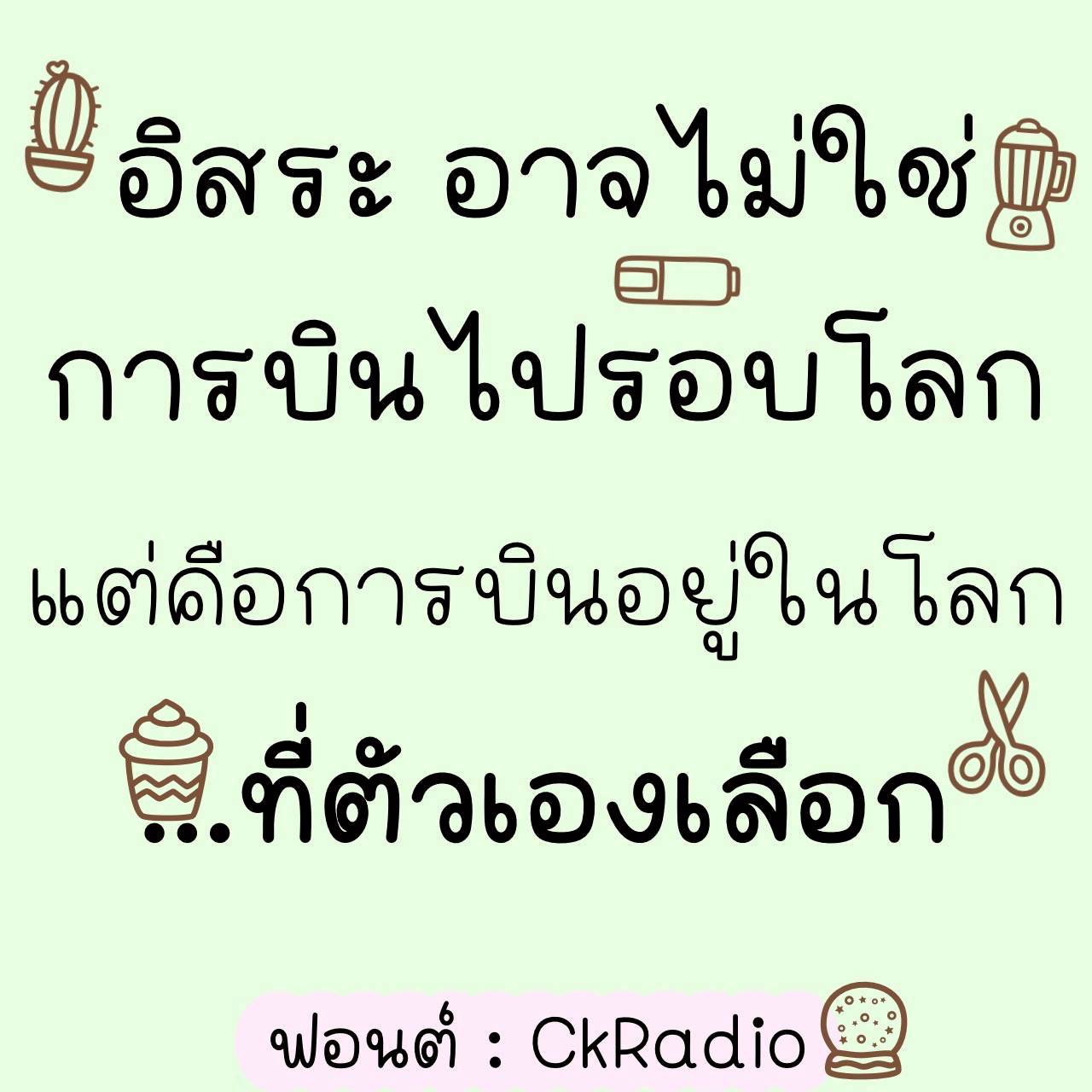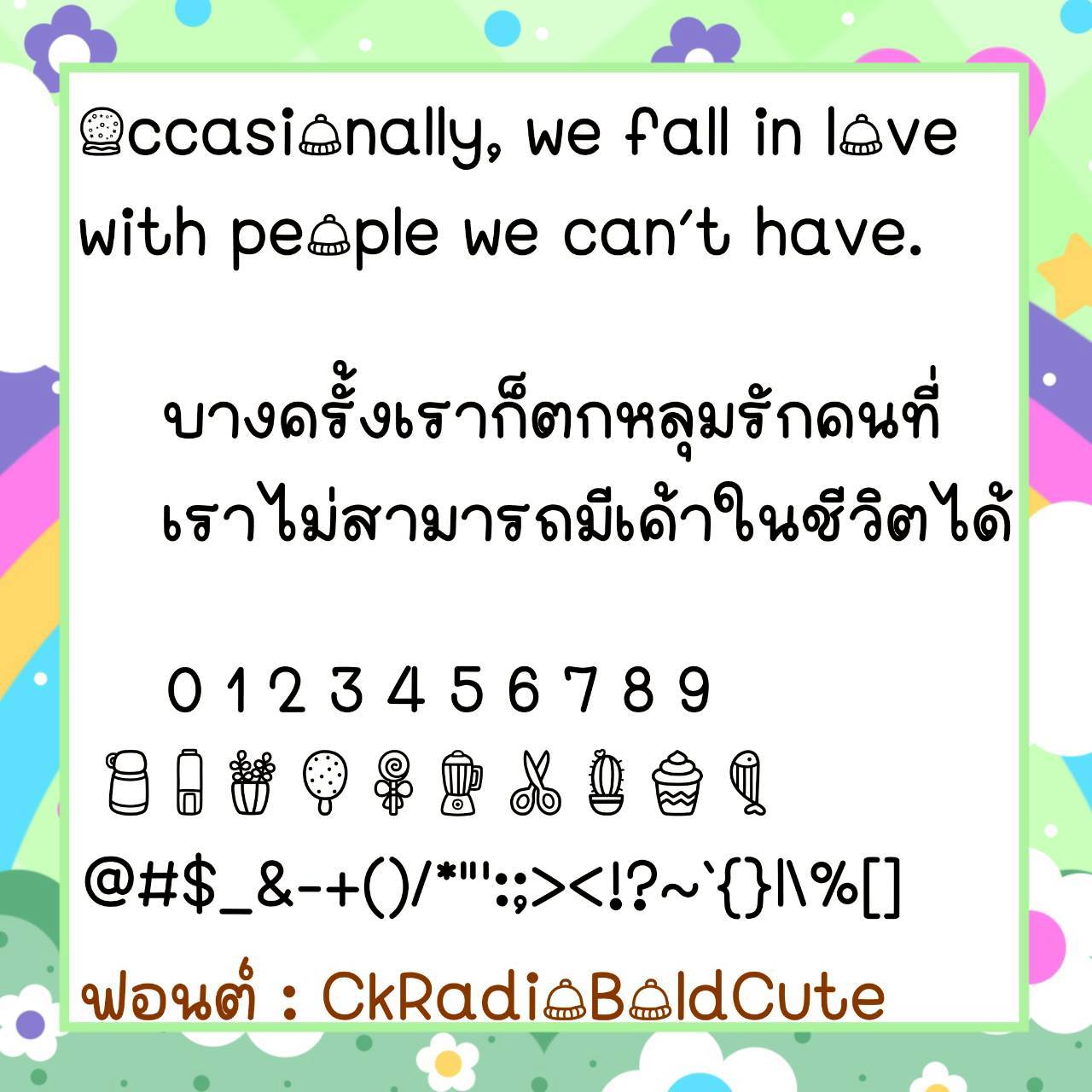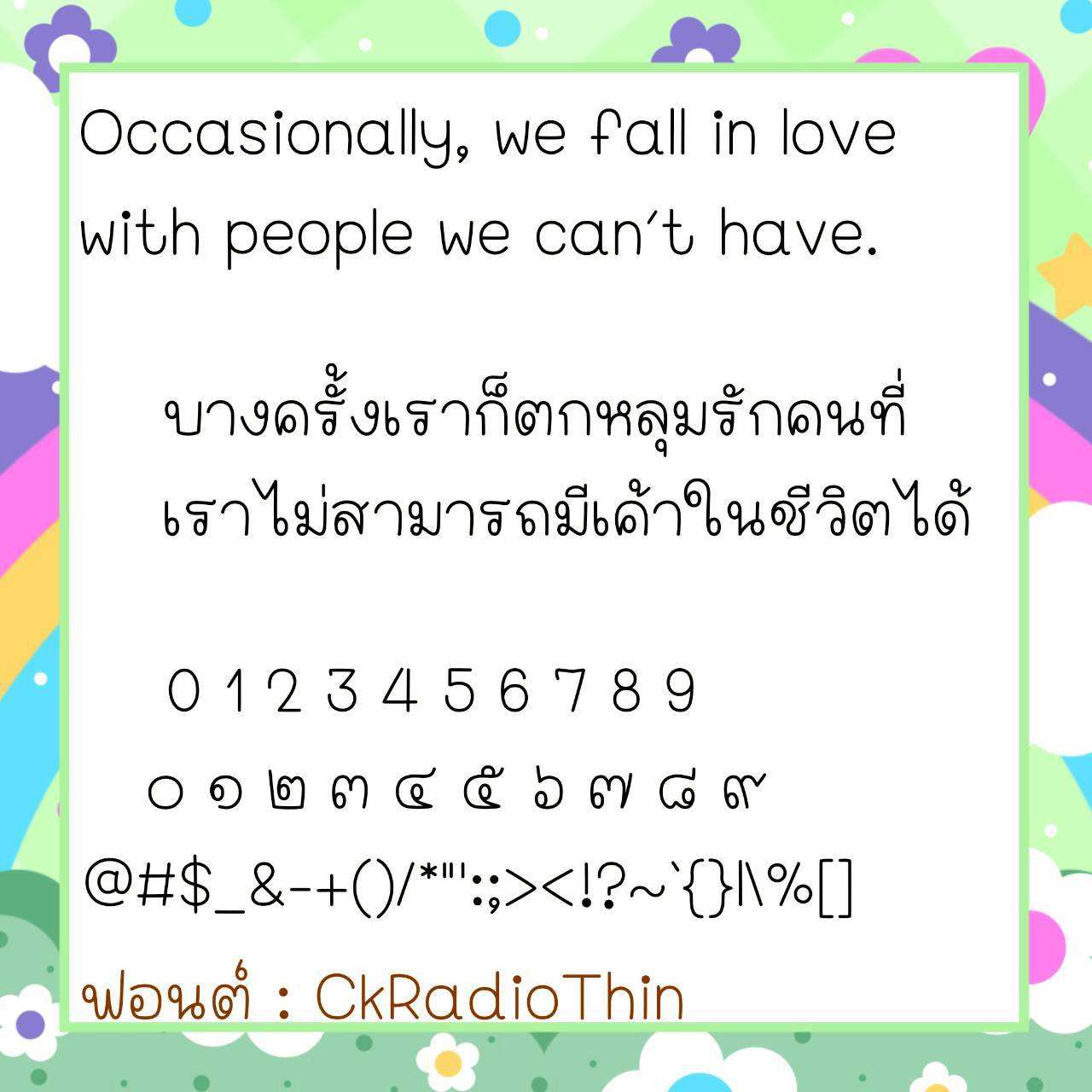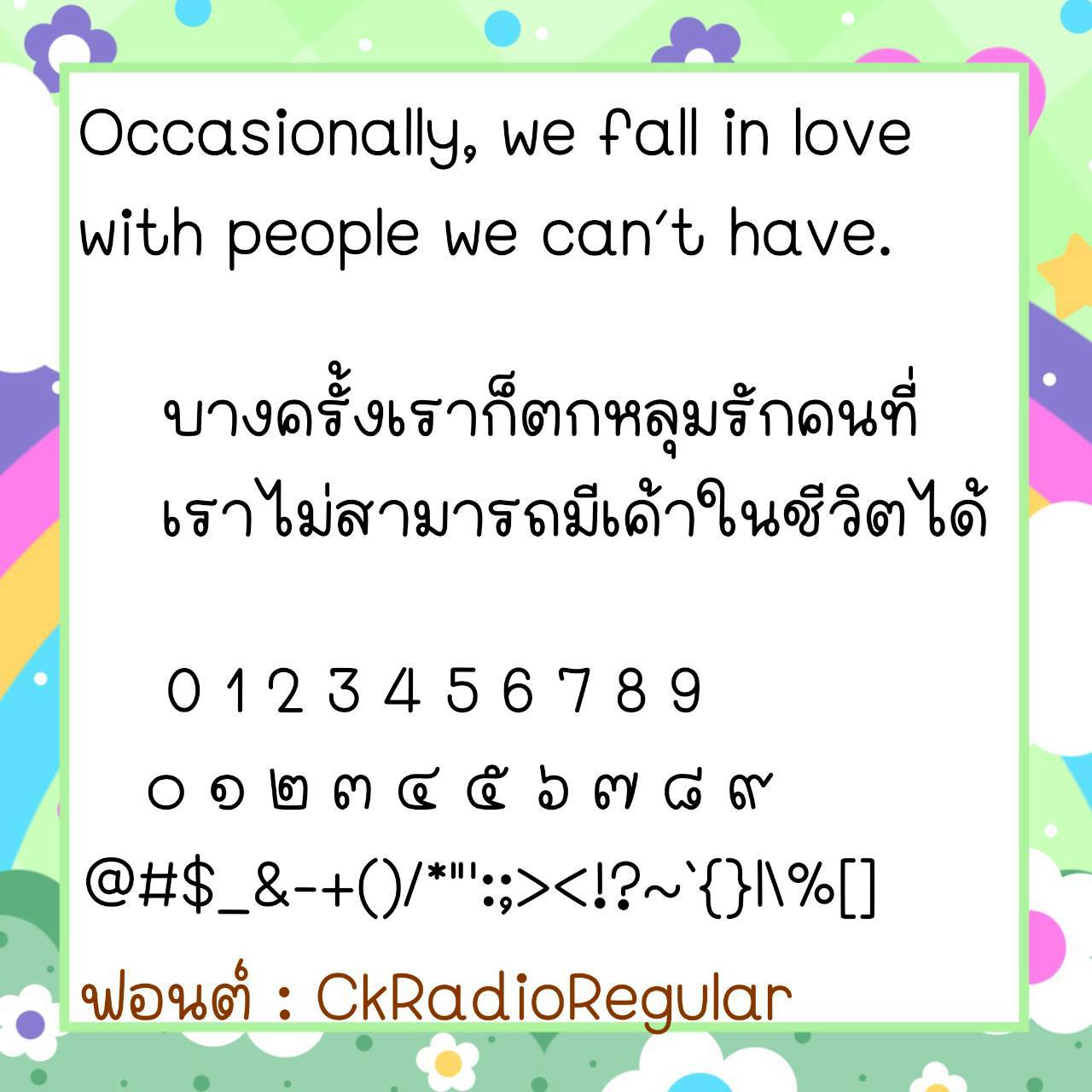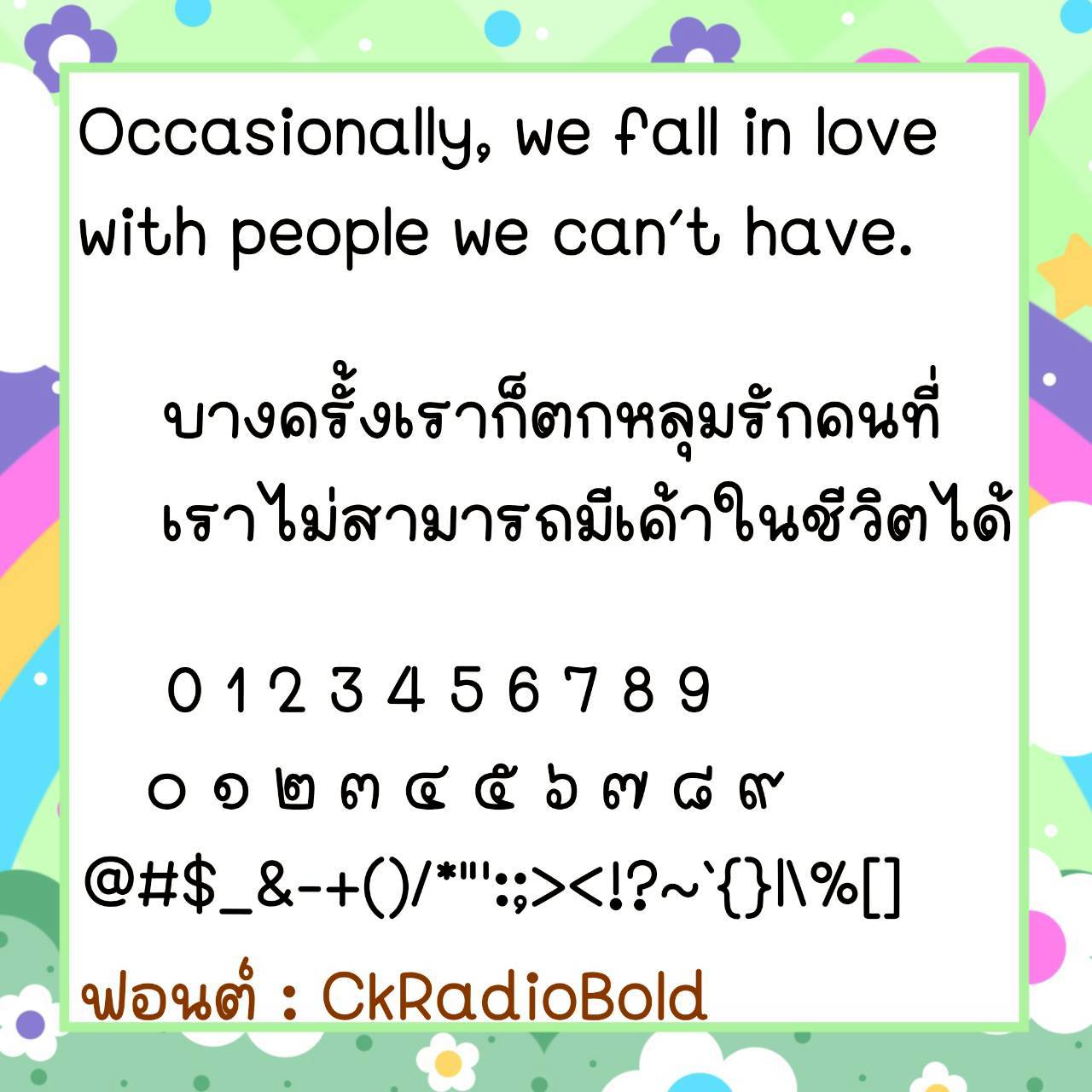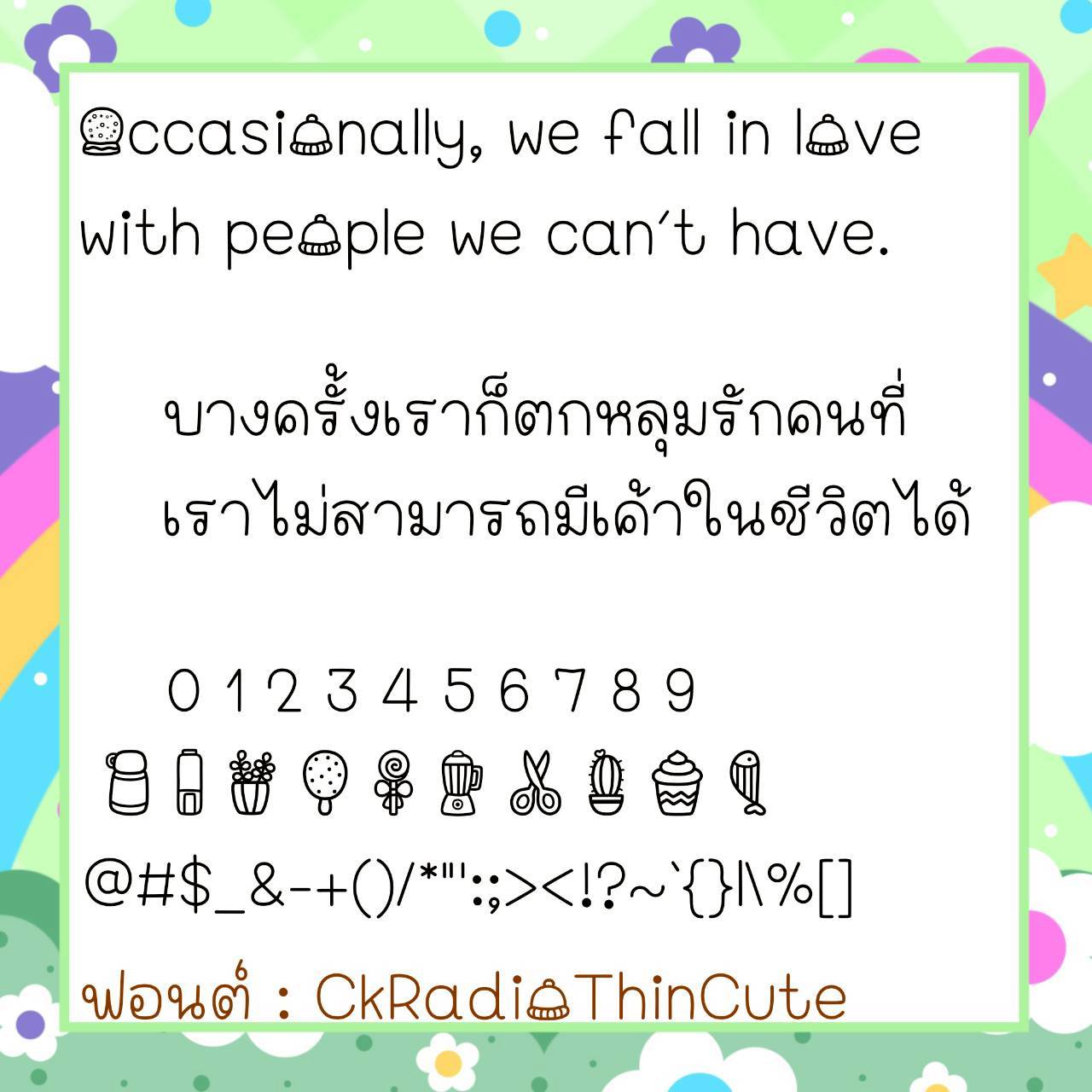
Font CkRadio
🔸 ฟอนต์ลายมือแนวตัวกลมหัวฟอนต์วงรี เน้นตัวอ้วนใหญ่ อ่านง่ายสบายตาดีต่อสายตา และยังมีไฟล์อิโมจิน่ารักๆ ที่ใช้แทนเลขไทยให้ด้วยค่ะ 🥰💙
🔹 This handwritten font features a rounded, oval font head, emphasizing bold, large characters. It’s easy to read and pleasing to the eyes. It also includes cute emoji files that can be used in place of Thai numerals. 🥰💙